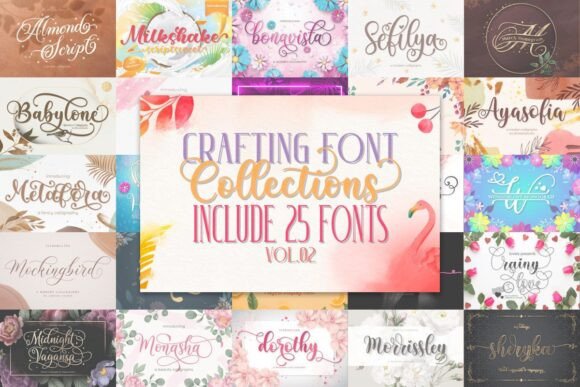
Crafting Font Bundle Vol.02
Jika Anda mencari aset berkualitas tinggi seperti Crafting Font Bundle Vol.02, paket premium ini adalah pilihan fantastis untuk proyek kreatif Anda.
Dibuat dengan presisi, Crafting Font Bundle Vol.02 menyediakan vektor yang bersih, tipografi yang halus, serta lisensi komersial untuk ketenangan pikiran Anda.
Baik Anda membuat produk POD (Print on Demand), undangan pernikahan, atau grafis media sosial, Crafting Font Bundle Vol.02 adalah pilihan yang sangat ideal.